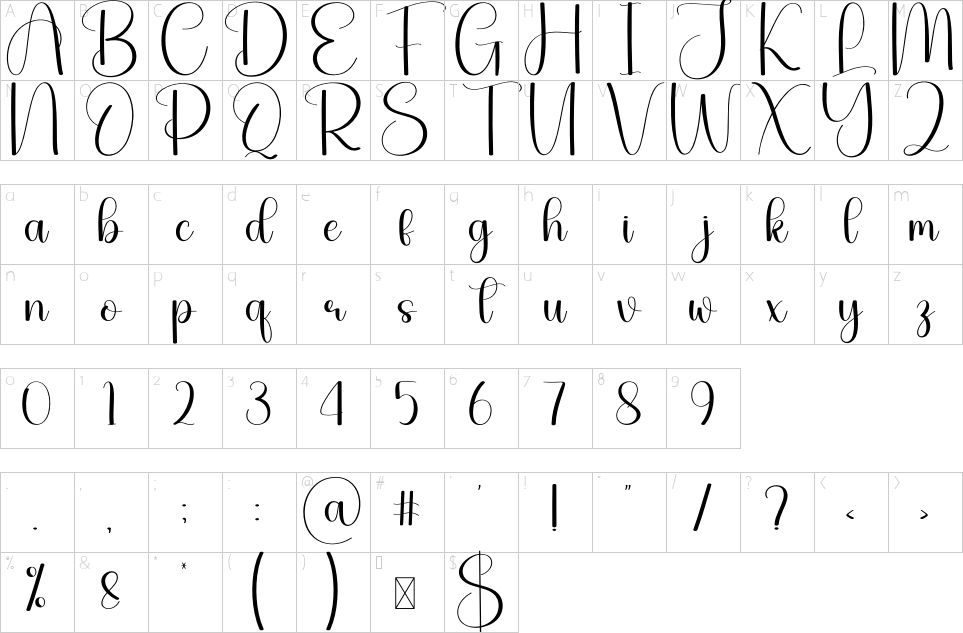
Aqui está uma descrição em português para a página de download da fonte ‘Photography Font | 1001 Free Fonts’, de forma envolvente e natural, sem inventar características ou usar markdown: Essa fonte ‘Photography Font’ é perfeita para fotógrafos e designers gráficos. Ela foi criada por scratchones e já foi baixada mais de 775 vezes. Para usuários de Windows e Mac, esta fonte de câmera é ideal para personalizar textos em seu trabalho, dando um toque especial aos seus projetos. Se você está procurando por uma fonte com um estilo que ajude a destacar suas fotos, esta é uma ótima opção. A qualidade e a facilidade de usar fazem dela uma fonte indispensável para qualquer profissional de design gráfico. Descarregue hoje e dê um toque único à sua próxima edição de fotos.